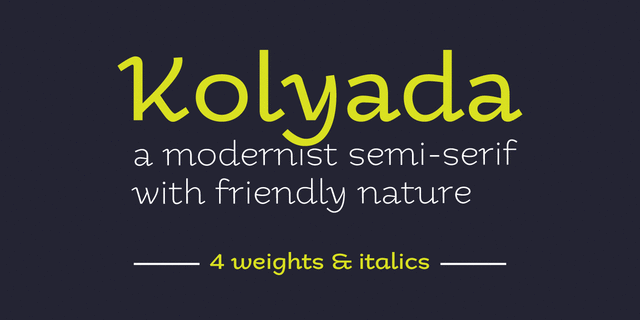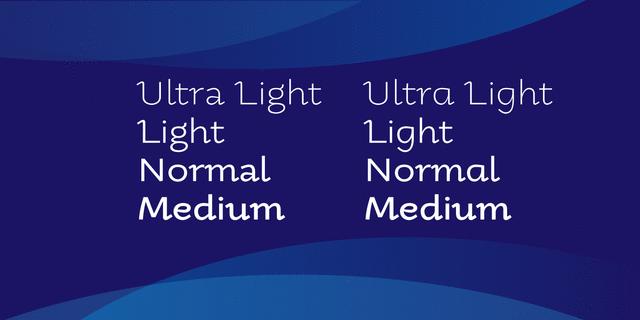
Коляда – современный антиква-гротеск с дружелюбным характером. Этот шрифт подходит для использования в торговле, рекламе, журналах, логотипах, книгах и т. д. Он поставляется в 4 вариантах жирности от Сверхтонкого до Среднего с натуральным прямым курсивом для каждого. Шрифт был разработан Кириллом Ткачевым в 2013 году.
Ассоциации c начертанием Kolyada LightКачества и характер:
свежий, лихой, развязный, легкий, тонкий, светлый, природный, натуральный, остроумный, живой, органический, оригинальный, самобытный, честный, характерный, этничный, традиционный, казацкий, вольный, колоритный, артистичный, художественный, динамичный, свободный, интересный, аккуратный, гуманитарный, доброжелательный, рукотворный, ритмичный, открытый, доверительный, выразительный, культурный, ремесленный, прикольный, весенний, племенной